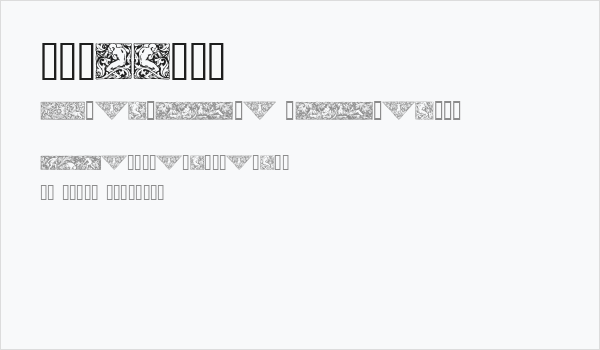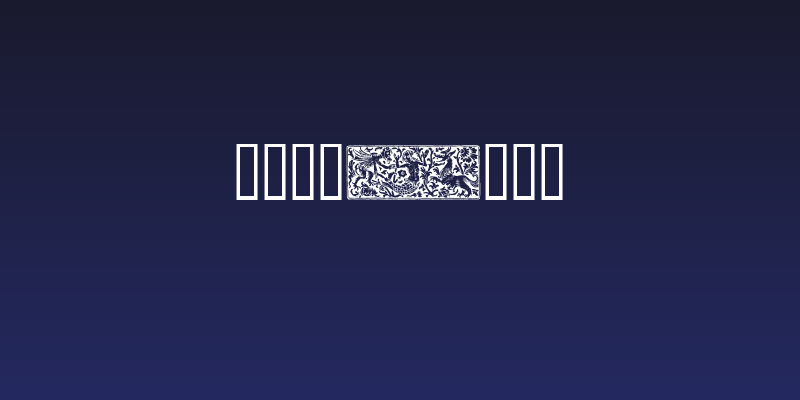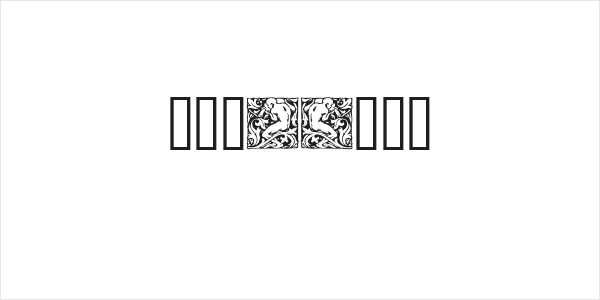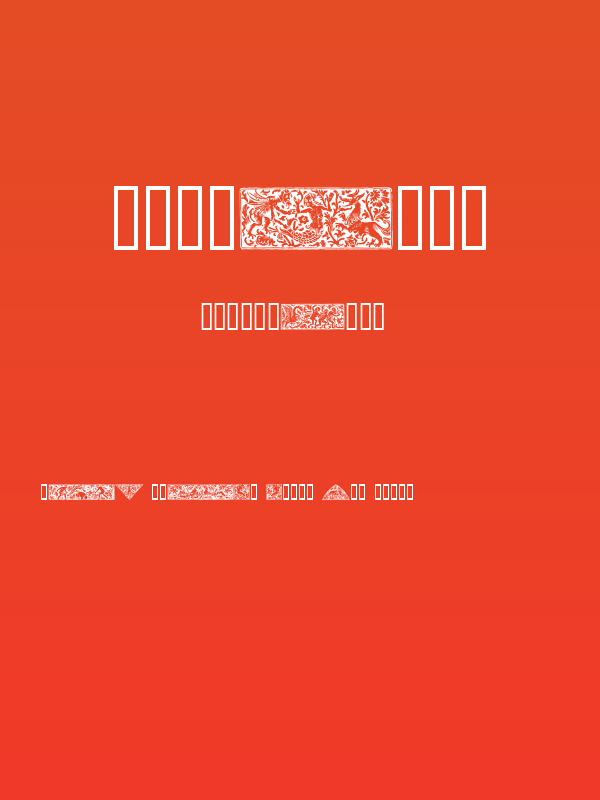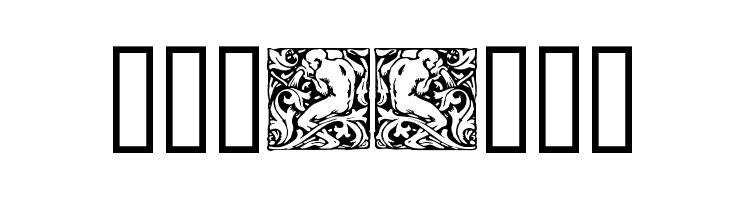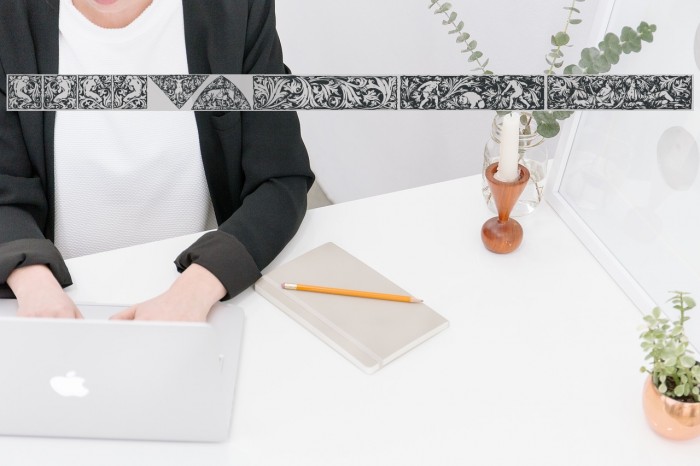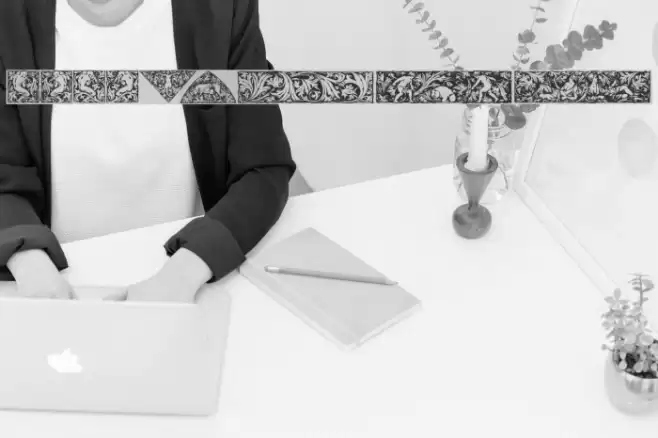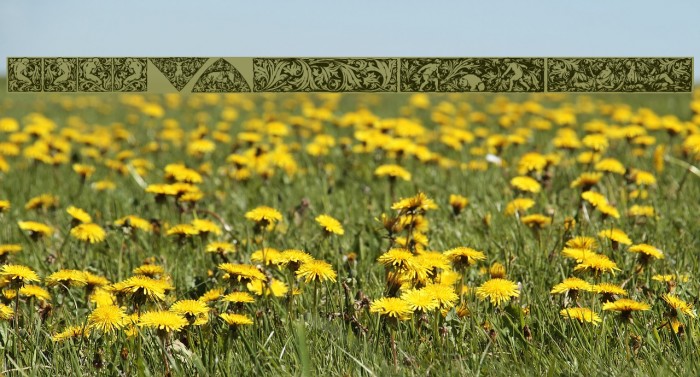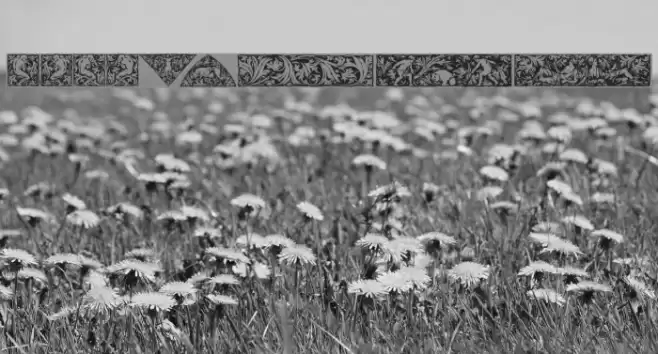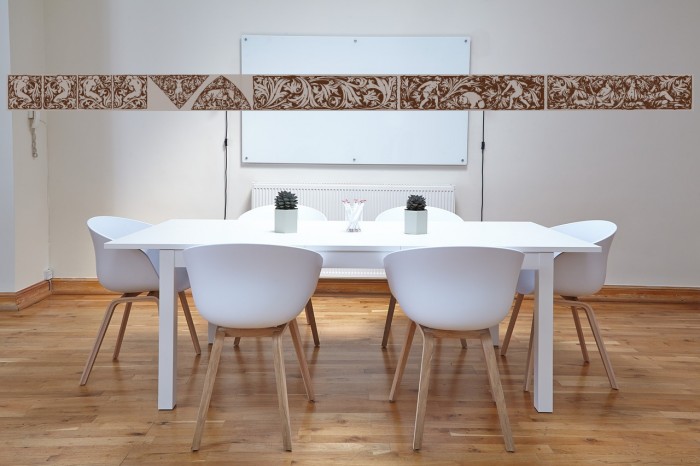
Woodcut1 Font
| Stil general | Vintage, Decorative |
| Caz de utilizare | Headlines, Logos, Decorative elements |
| Proiecte propuse | Ideal for vintage-themed posters, artistic book covers, decorative invitations, and branding that requires a historical or artistic touch. |